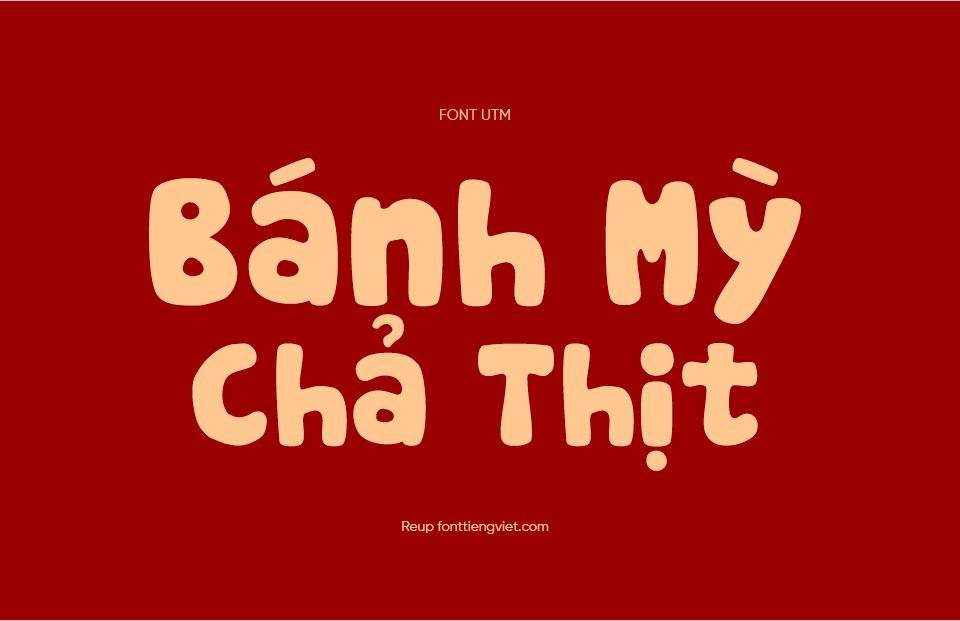
Font việt hóa UTM Cookies
Font việt hóa UTM Cookies: Lựa chọn hoàn hảo cho thiết kế sáng tạo
Trong thế giới đồ họa hiện đại, việc tìm kiếm một bộ Font Miễn Phí chất lượng luôn là ưu tiên hàng đầu của các bạn học sinh và giáo viên. Font việt hóa UTM Cookies nổi lên như một ứng viên sáng giá nhờ phong cách thiết kế mềm mại, thân thiện và đầy tính nghệ thuật. Được biết đến với các đường nét bo tròn đặc trưng, bộ font này mang lại cảm giác ngọt ngào giống như những chiếc bánh cookies, giúp các sản phẩm học đường trở nên sinh động và gần gũi hơn bao giờ hết.
Ưu điểm nổi bật của Font việt hóa UTM Cookies
Thiết kế độc đáo và dễ đọc
Đặc điểm lớn nhất của Font việt hóa UTM Cookies chính là sự cân bằng giữa tính thẩm mỹ và khả năng đọc hiểu. Dù sở hữu các nét chữ có phần tinh nghịch, font vẫn đảm bảo độ rõ nét khi in ấn trên giấy hoặc hiển thị trên màn hình máy tính. Điều này cực kỳ quan trọng đối với các bạn học sinh khi làm slide thuyết trình hay trang trí báo tường, giúp nội dung truyền tải mạch lạc nhưng vẫn giữ được dấu ấn cá nhân độc đáo.
Khả năng ứng dụng đa dạng trong giáo dục
Với bộ mã Unicode đã được Việt hóa chỉn chu, bạn sẽ không còn lo lắng về lỗi font khi gõ tiếng Việt có dấu. Font việt hóa UTM Cookies thường được ứng dụng để thiết kế thiệp mời, bìa sách bài tập hoặc các bảng tin lớp học. Sự linh hoạt này giúp thầy cô dễ dàng tạo ra các bài giảng trực quan, thu hút sự chú ý của học sinh một cách tự nhiên nhất.
Cách sử dụng và lưu ý khi thiết kế